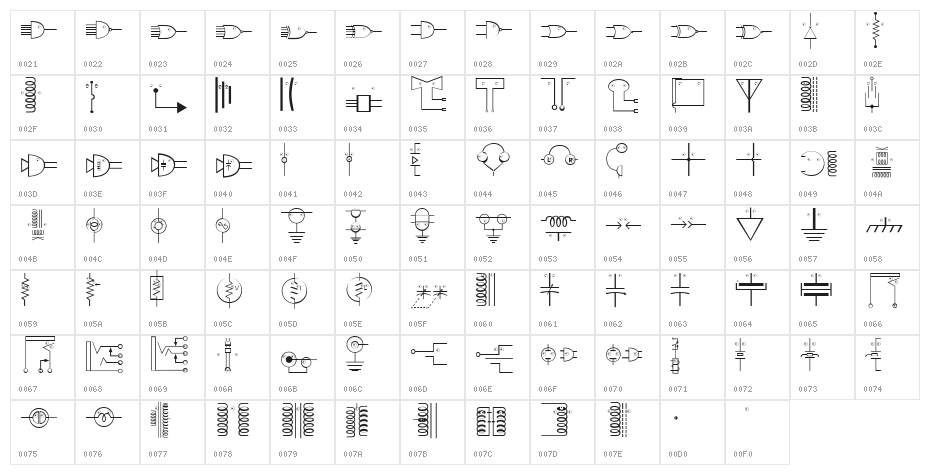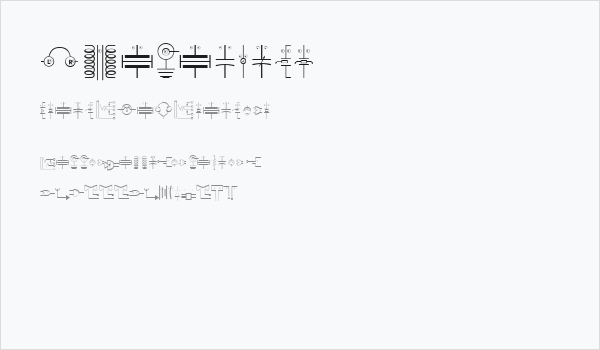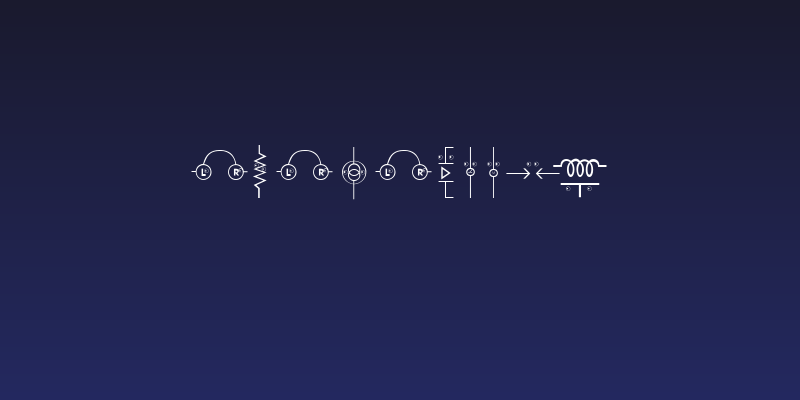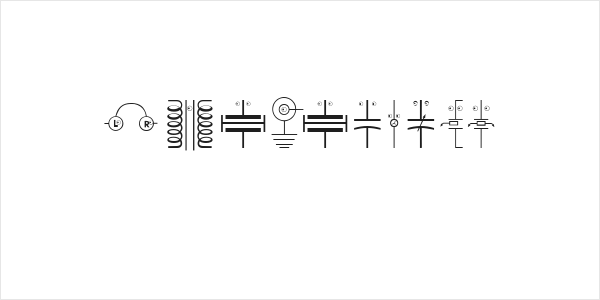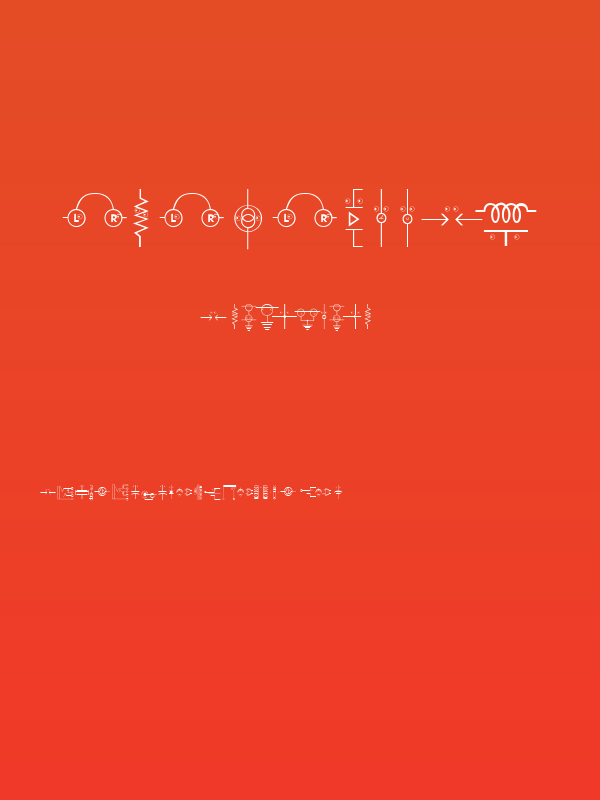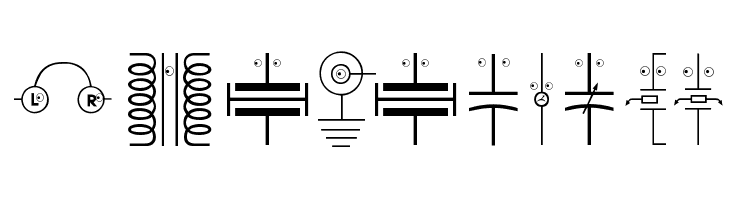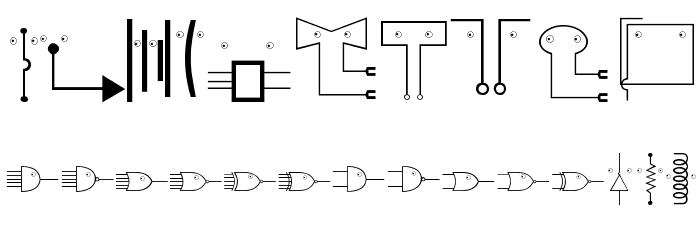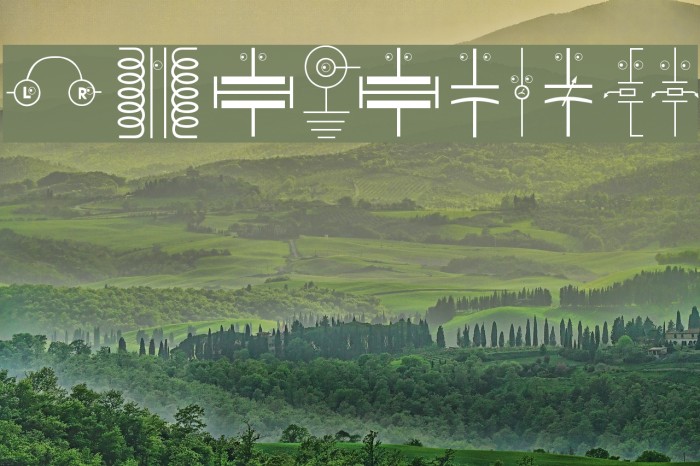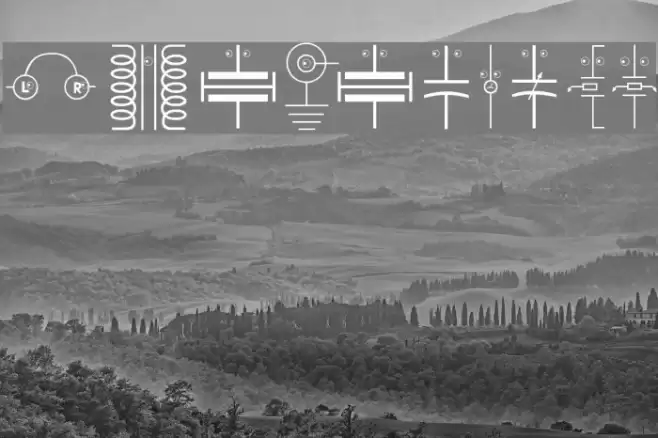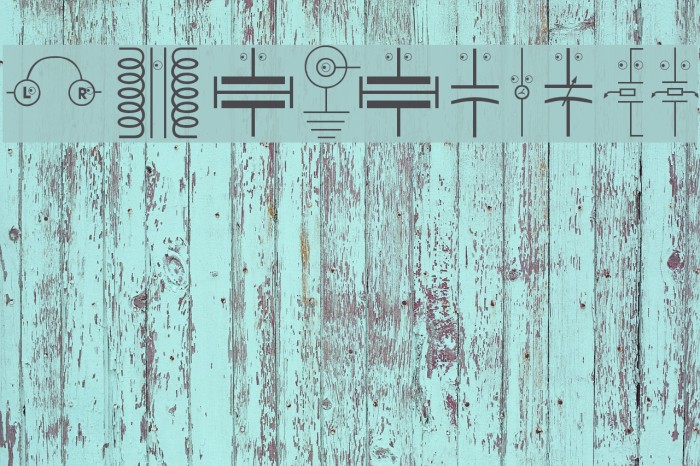
EyelecBats Font
| 全体的なスタイル | Technical, Schematic |
| 用途 | Decorative, Technical illustrations |
| おすすめプロジェクト | Ideal for educational materials in electronics, technical illustrations, engineering presentations, and themed graphic designs. |